一个主题,各自表述。
同一道风琴闸,呈现五位设计师手笔。湾仔港湾消防局因为髹上「消防局 FIRE STATION」特色字体而引人举机留影。创意可以令庄重正经的公营机构变得亲切活泼。湾仔多个公共空间一样给活化,惊喜排住队来,所为何事?
拍摄当日为早上10时许,经过港湾道消防局的人不算多。低头的依旧低头,急步的继续急步,反而消防局对面马路,有两位泰籍游客为这道不一样的闸门拍了照。
五位平面设计师在红色风琴闸门上,重新设计「消防局」的中英文字体,凸显香港独特的双语设计。这是「#ddHK设计#香港地」活动的一部分,湾仔是首个试点,多条街道、行人天桥、电车站等都有新貌。
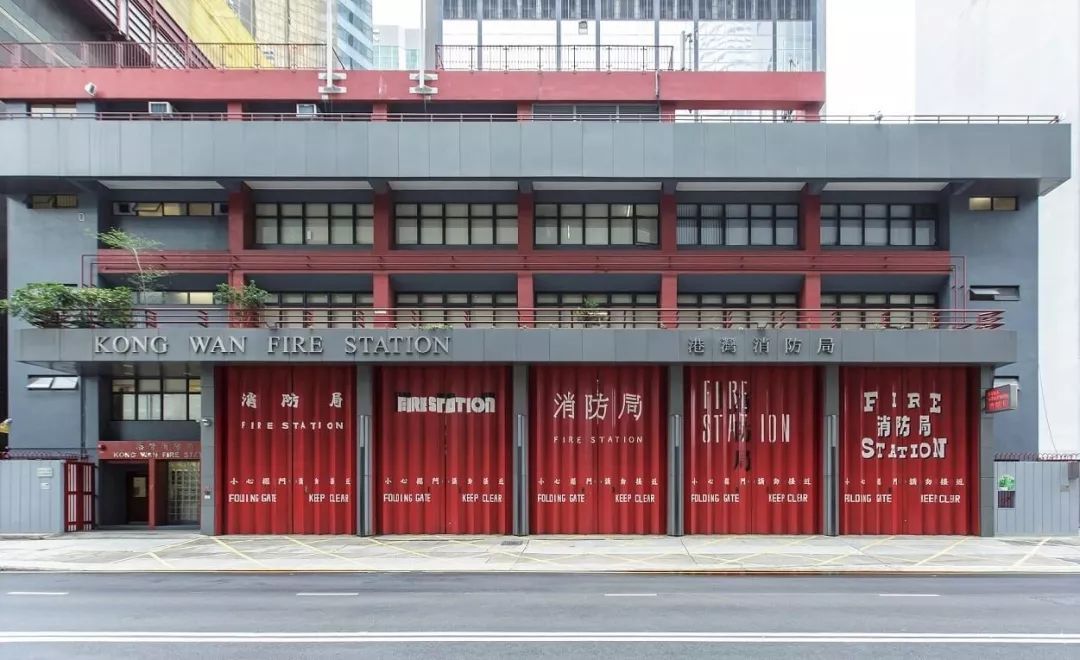
港湾消防局的独特字体由即日起展至2021年2月。
设计师蔡剑虹的作品中英相叠,把英文字母变成中文笔划。「消防局」若隐若现,要多花眼力才看到,十分玩味,原来作品有个廿分玩味的前身。「意念是用一条消防喉捆出『消防局』三个字,但消防局觉得感觉太年轻太cute,想稳重一点。」他坦言早料到他们不会采纳,但又觉得「何妨一试」 ?幽默的他笑说:「试下人家底线嘛,一开头就交出最大路最保守,人家就不用找我啦﹗」站在设计师角度,他觉得做些消防局没试过的东西,对比有趣得多。「当然我要顾及他们的想法。」
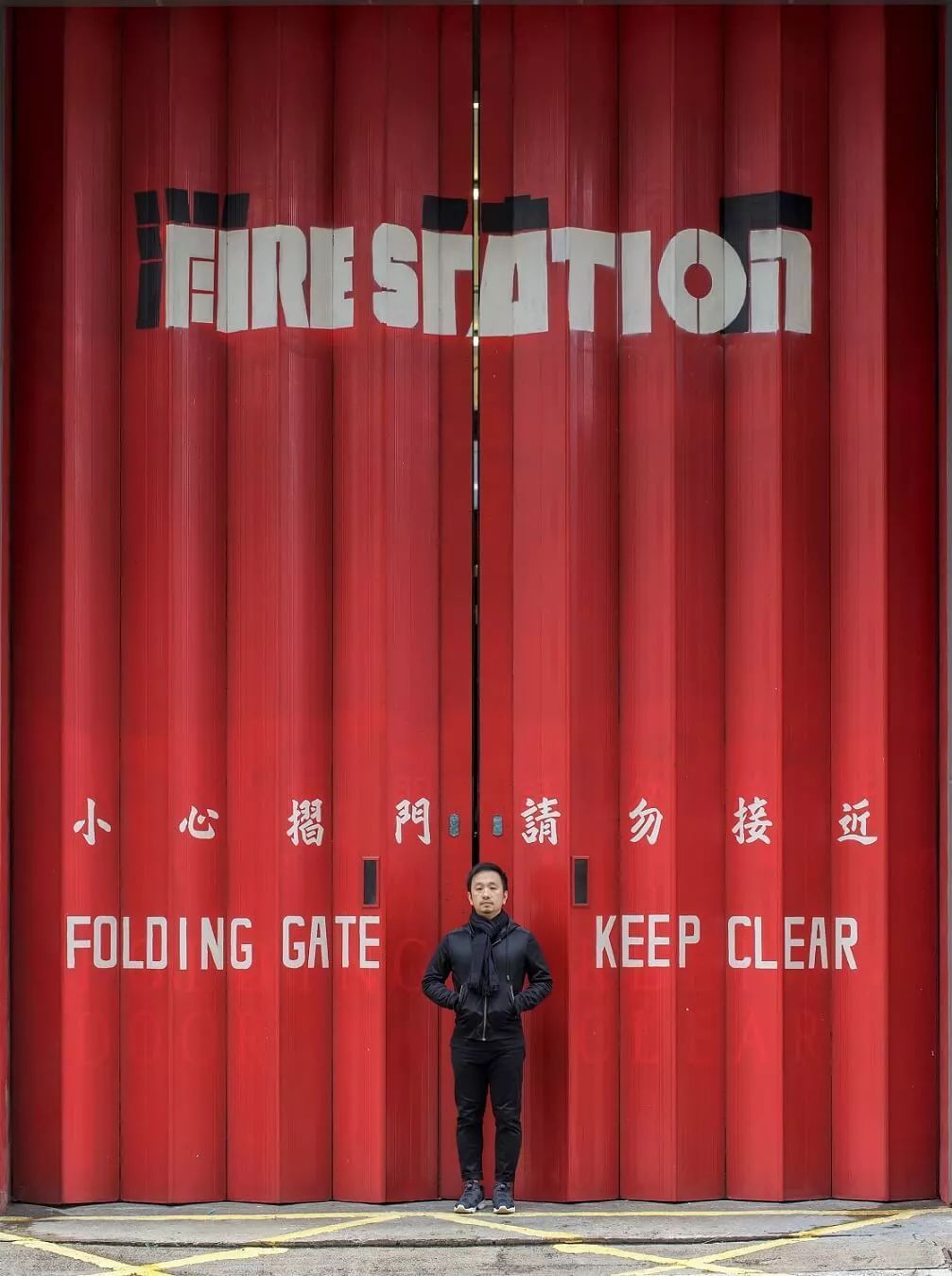
蔡剑虹的作品不拘泥于笔划清楚与否,他认为即使观者觉得「唔靓」或「其他字靓过呢只字」都没所谓,留伏线让人发现细节才重要。
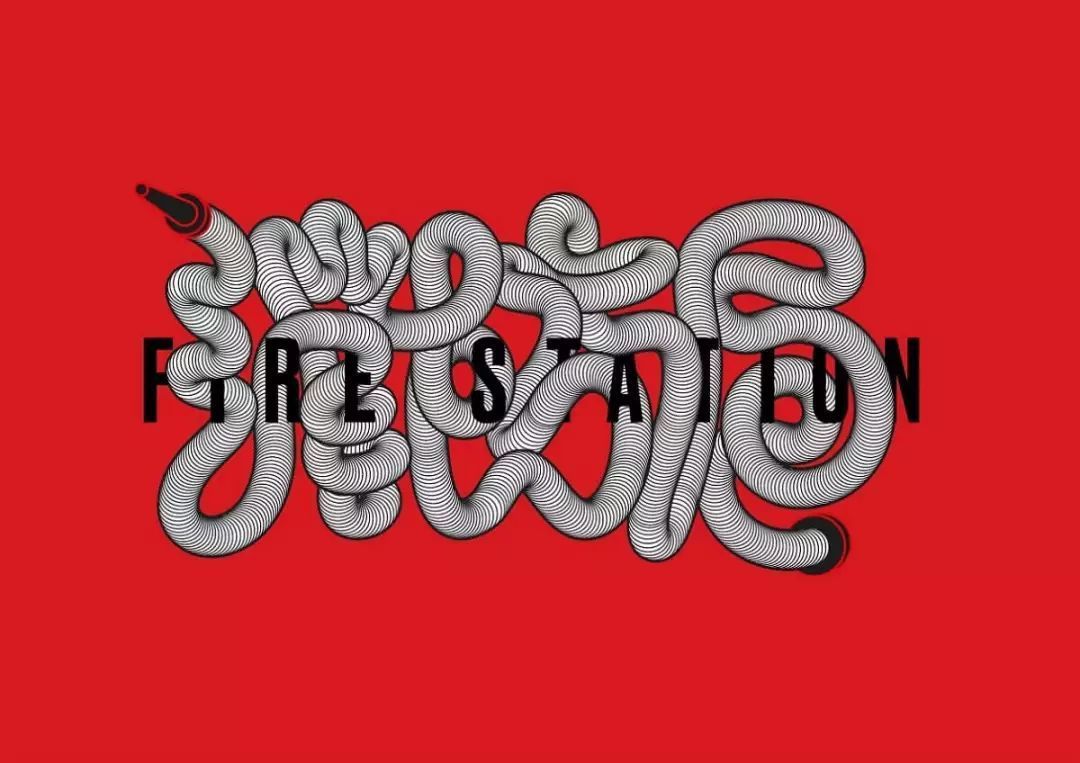
蔡剑虹的第一稿意念年轻活泼,但当局希望设计能稳重一点而没采纳。
清楚与写对非重点
考虑到香港中西交汇的文化背景,他把中英文字混杂在一起。「几位参与的设计师本身多专注于字体创作,他们的作品既靓也具功能性,我的比较视觉化,易读不是我的首要考虑,反正人人都知那是一间消防局,我又何必写得清清楚楚呢?即使大家觉得消防局三个字『都不似慨』,我觉得没所谓。」引起大家好奇,疑惑黑色的部分是什么,是他的把戏。「想大家停低脚步细看。你不能永远站在观者侧边解释,只能让设计自己发酵。」他也不执着所谓的笔划对错。「五六十年代的手写招牌字,有些是专登把笔划结合,利用减笔展现个性。我认为美术字大概睇到形态就够,引发到讨论更好。」
他笑指只要有公众参兴,公营机构就不介意作品美观与否,反而找专业人士设计,就会设很多框架。「他们会立即谂work唔work,会跟设计师倾很多条款。」他续指设计师很多时都要援引成功例子加以说服,所以今次合作确是美事一桩。
设计不应放在博物馆孤芳自赏,在社区更能发挥作用。「五幅字体作品这样放出来,一定震撼的,我相信它有感染力,对社会和谐有帮助。」
电影感字体最夺目
记者认为本身为字体设计师的郭家荣作品在风琴闸上最为抢眼,字体带一点戏剧性。原来字体真的脱胎自一出戏。年前他为电影《古巴花旦》海报做字体设计,参考了很多六七十年代的娱乐杂志封面。「当年很多粤剧明星会登上杂志,杂志会为访问造些独特字体,我参照那些设计做了几个作品,找我的海报设计师胡卓斌选了其中一款。」那就是他现在置于消防局那只字体”Urushi”的雏形。「字形比海报上的收窄了。」
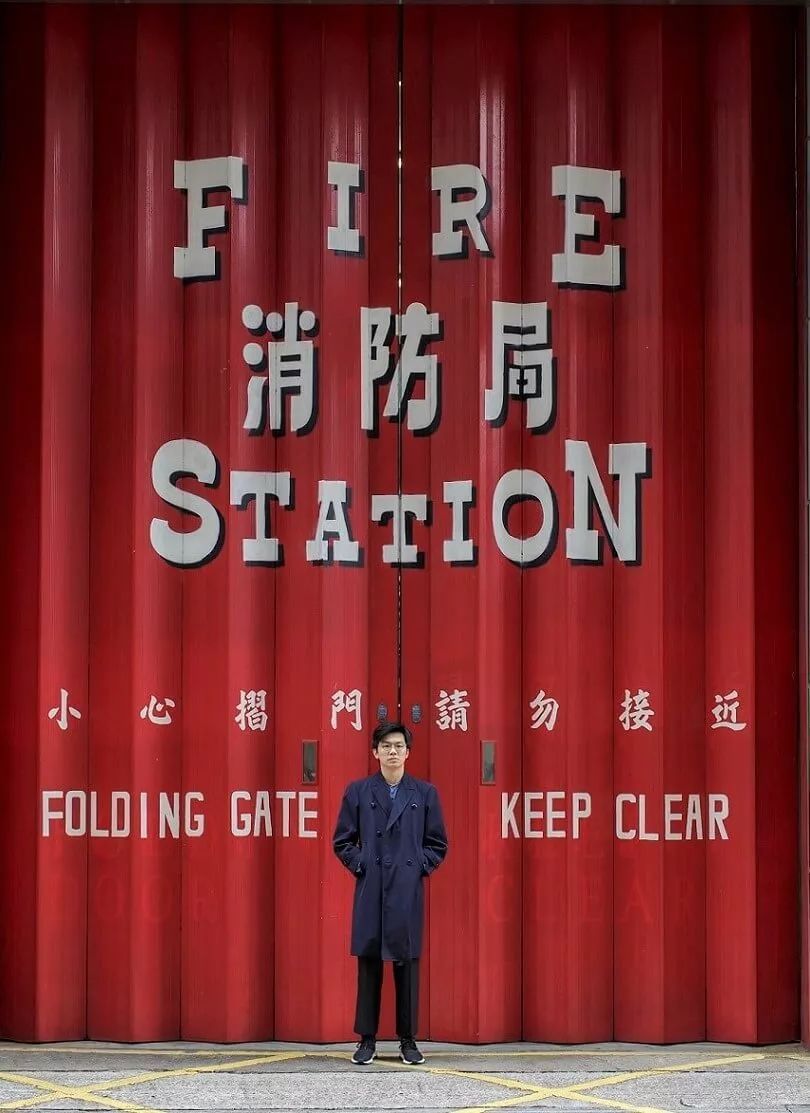
曾到英国攻读字体设计硕士课程的郭家荣专注于字体设计范畴,现正努力开发其“Urushi”字体。
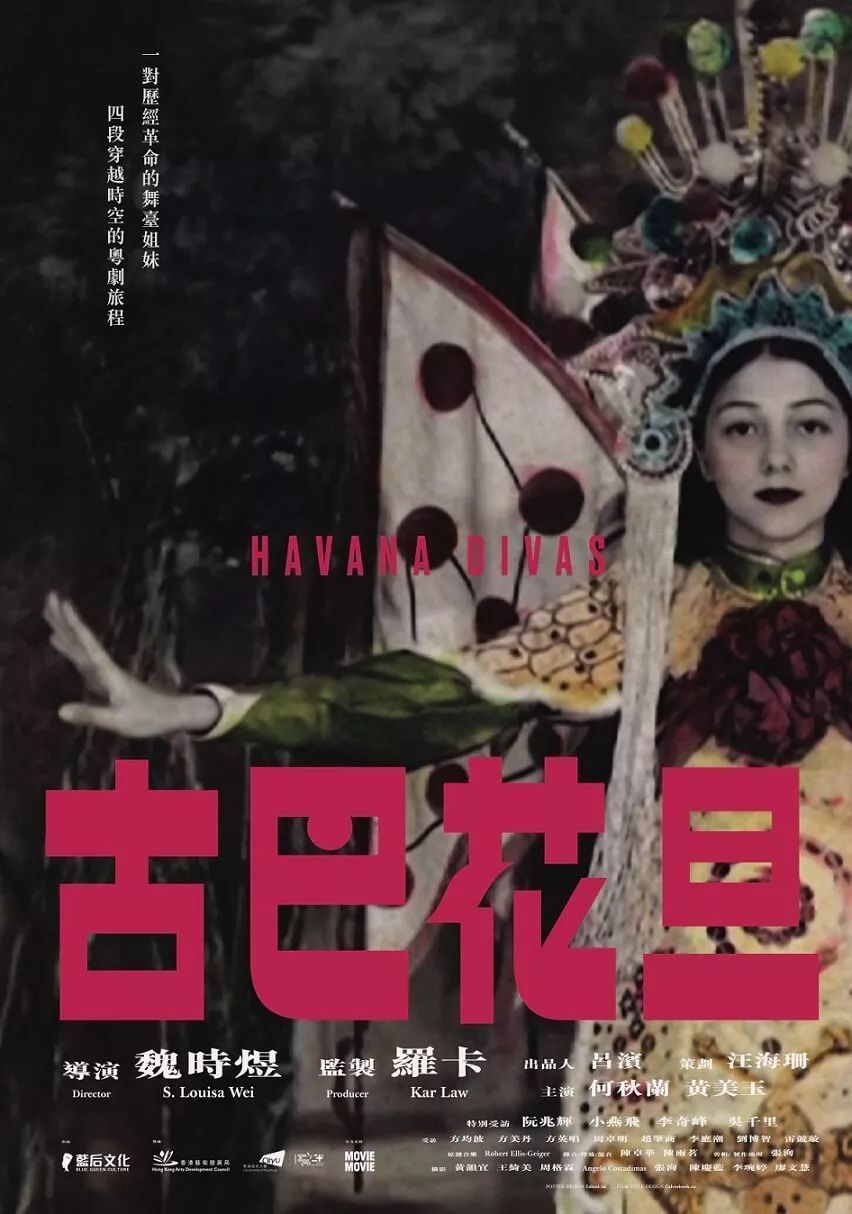
郭家荣去年为纪录片《 古巴花旦》海报做戏名字型设计,参考了一大堆旧娱乐杂志的美术风格。
提到字体设计就侃侃而谈的他,肉紧的说老早对消防局的风琴闸产生兴趣。「唔系为今次设计作古仔,我本身经过湾仔同铜锣湾消防局真系会停低望个闸,一来觉得个form好靓,二来留意到上面字体本身比较传统,好富香港特色,我曾经影过相。」他形容闸门有点像舞台的红色绒布幕,但不想把字体造得夸张,只做了个画龙点睛的动作。「字本身已经很playful了。外国的消防局都会把头尾英文字母加大少许,我也参考了他们的设计。」
他的” Urushi ”字体仍在开发中,英文及日文仮名都已造好,并放在美国卖字网站Future Fonts上寄卖,中文字数量则不多。「如果有人要用某些中文字,我可特别造。这款字体适合大型display,远距离都能看清,跟消防局这个企划几夹。」他认为香港的大型广告字体选择不足,锐意改变现状。「赚不赚钱都好,都希望多造些设计出来让人用。」
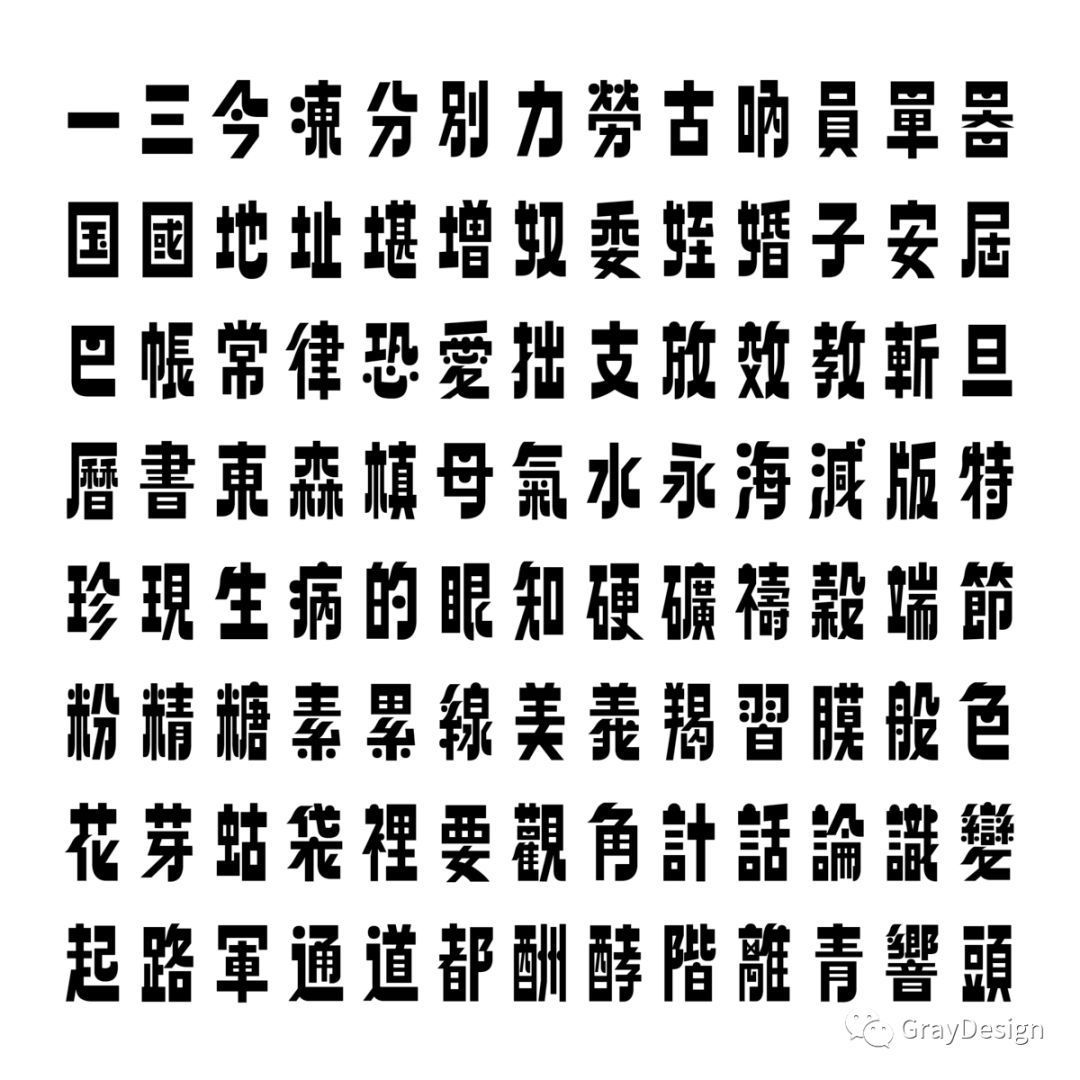
“Urushi”的中文字可供订造。
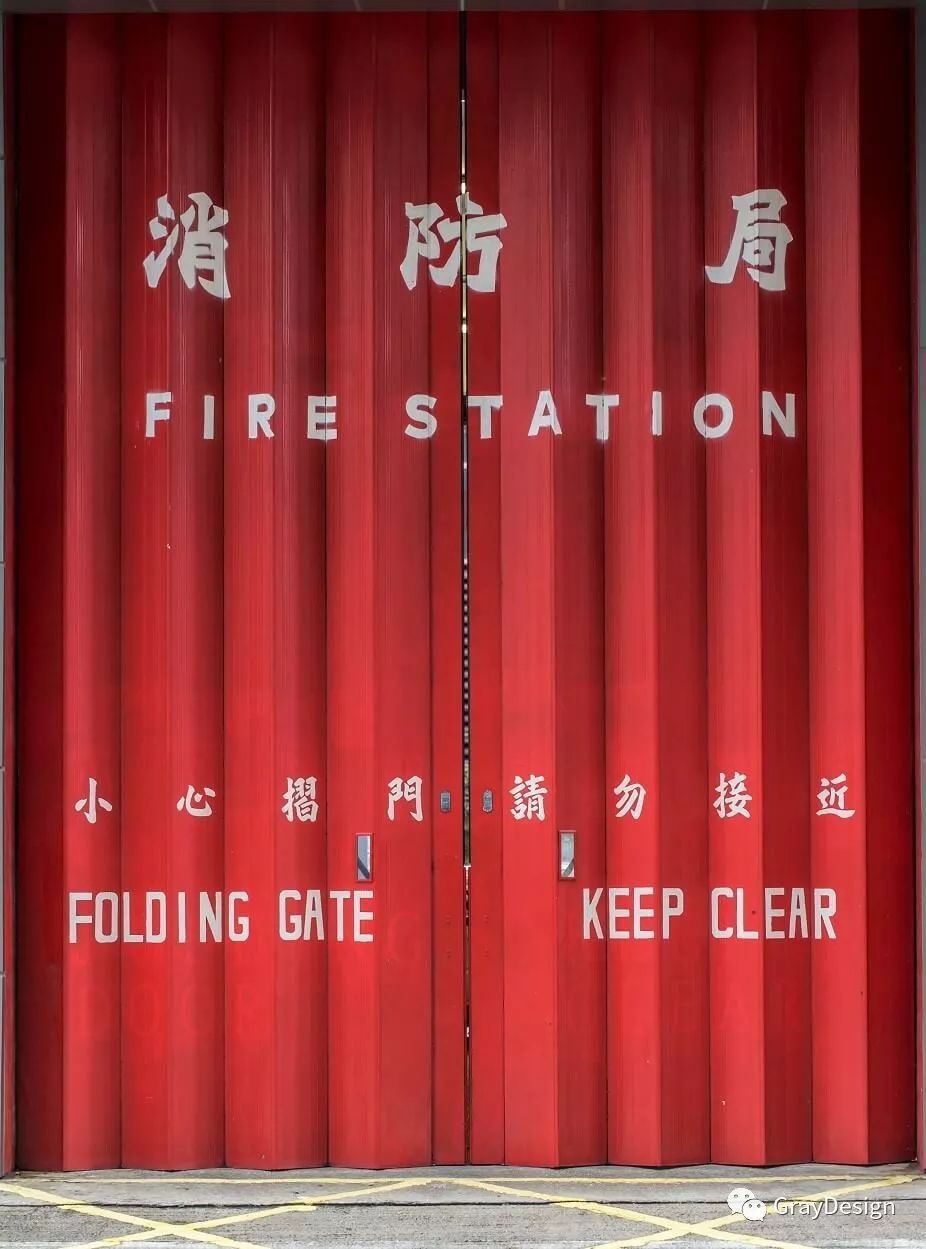
陈濬人2012年起研究「香港北魏真书」风格。这种字体早年散见于招牌、产品包装、告示等。他利用此带刚猛之劲的字型勾画「消防局」三字,以字体显出消防局之效率。
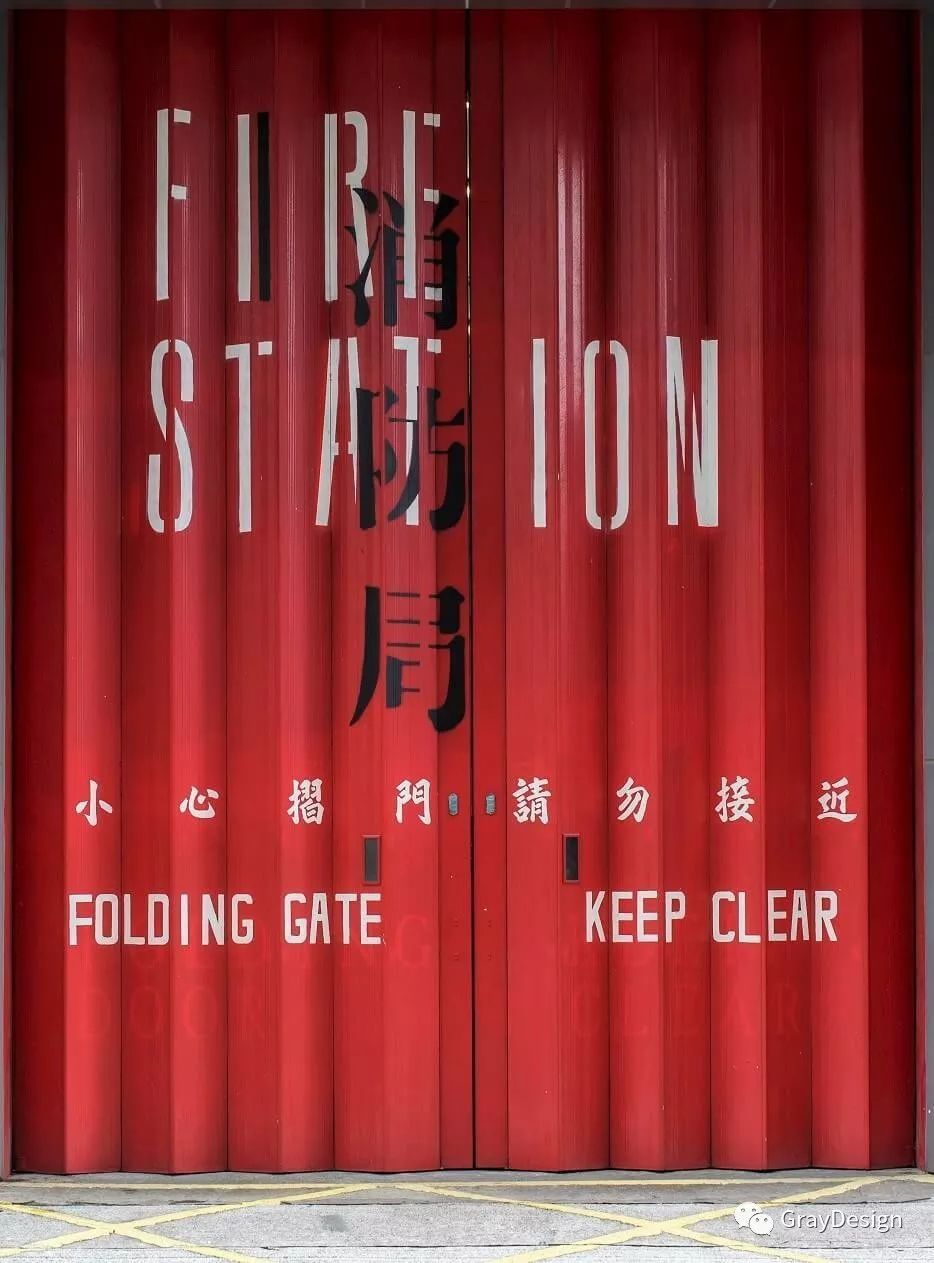
胡卓斌认为中文与英文是少数相叠都能清晰辨认的文字。以往一些公共建筑墙身、街上的铁闸,甚至档案文件都有中英互相穿插及遮盖的情况,好像在争话语权。他把这种独特的「土生美学」应用在今次的设计上。
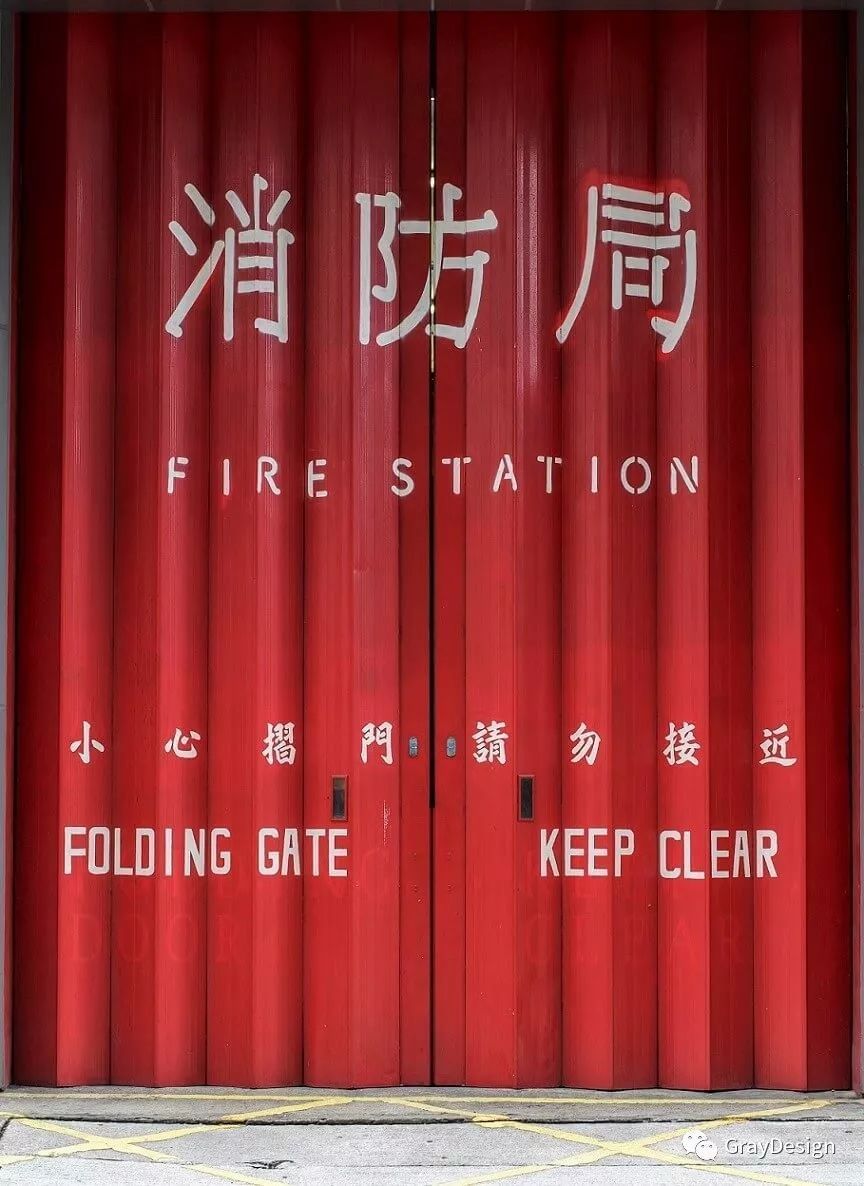
「锣机字」常见于工厦指示及告示牌。锣机 (Milling Machine) 配有360度旋转刀片,可于胶或金属板雕字,字尾端呈圆角。笔划会设计成纵、横线,避免过多交集,并尽量减笔,让师傅能一笔完成。麦綮桁制作的「机械明朝」字体传承自锣机字,但起、收笔加入上勾,仿造明体的小三角。他谓锣机字一直是配角,字型小,今次让它成为主角。